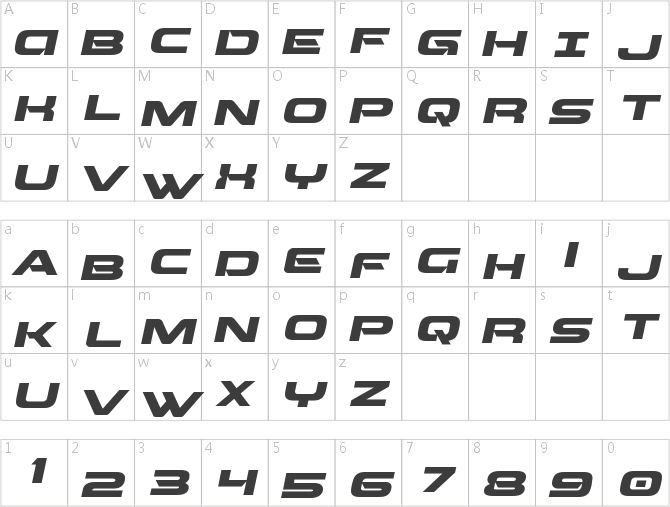
beamweaponexpandital 詳情頁(yè)
beamweaponexpandital字體字庫(kù)是一款讓人賞心悅目、百看不厭的英文字體,適合各類廣告和產(chǎn)品包裝設(shè)計(jì)應(yīng)用,字體大小0.03MB,格式為ttf字體,上傳用戶是sunlight,作者/版權(quán)方為未知